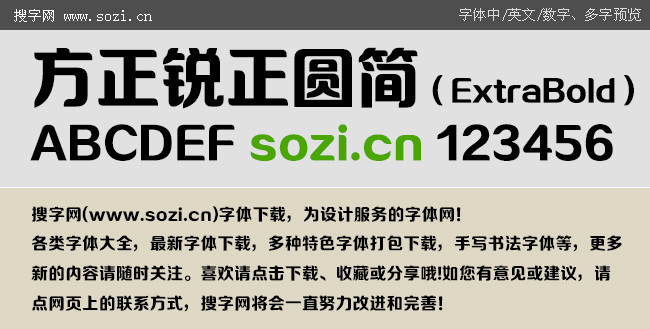
方正銳正圓簡(jiǎn)ExtraBold
搜字網(wǎng)提供一款方正銳正圓簡(jiǎn)中文字體下載,銳正圓系列是銳正黑系列的擴(kuò)展與延伸,屬性介于圓體與黑體之間,是適度中和的中性設(shè)計(jì),既有圓體的圓潤(rùn),又不失黑體的厚硬,柔中帶銳、圓中有方。筆鋒采用半圓角設(shè)計(jì),相較黑體、圓體更具圓潤(rùn)兼銳化的時(shí)尚度,而太過(guò)夸張時(shí)尚又有失莊重,故而有意做適度收斂,圓融時(shí)尚而又端莊穩(wěn)重,適用領(lǐng)域廣泛。